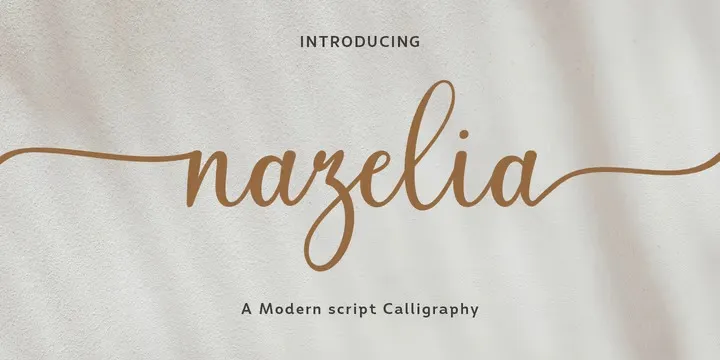
A Nazelia Font é uma elegante escolha para designers que buscam um tipo moderno e divertido. Criada pela Siwox Studios, esta tipografia de script oferece uma base linhas irregular que confere ao texto um toque único e vibrante. Perfeita tanto para uso cotidiano quanto para criação de trabalhos artísticos, a Nazelia é simplesmente acessível e prazerosa de usar. Ela vem com elementos modernos, handmade e limpos, incluindo suporte para desenhos alternativos e apoio internacional para a maioria dos idiomas ocidentais. Suas swashes proporcionam um toque de sofisticação, tornando-a uma opção perfeita tanto para headlines quanto para textos mais detalhados. A Nazelia é ideal para quem busca criar combinações memoráveis em seus projetos de design gráfico. Essa fonte será uma excelente adição à sua colecção, adicionando um toque especial e moderno a qualquer projeto onde seja usada.